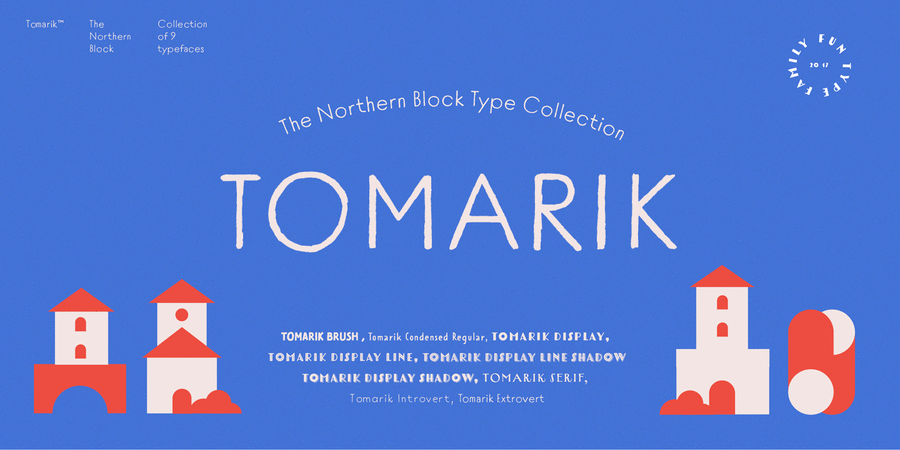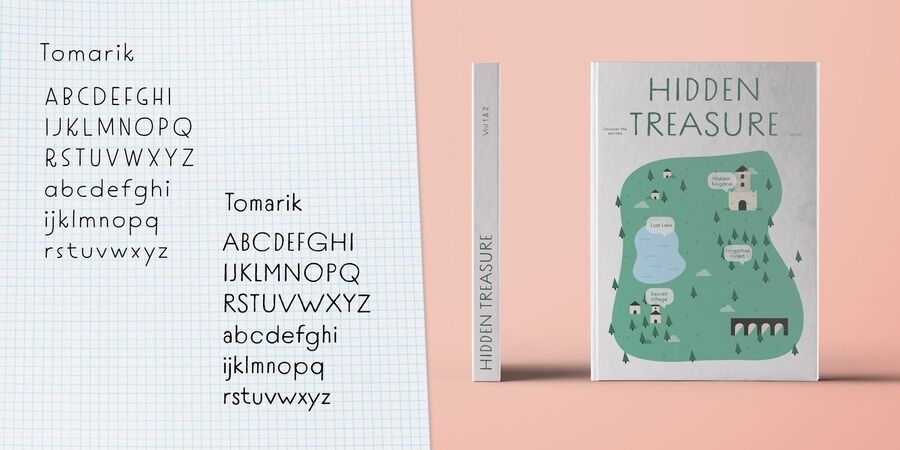
Tomarik Introvert (1 шрифт)
Закритий геометричний гротеск, намальований ручкою чи олівцем – частина яскравої колекції рукописних шрифтів Томарік. Грайливе доповнення будь-якого творчого проекту. Шрифтової набір, зібраний для роботи за принципом «обирай і змішуй», він пропонує велику різноманітність стилів і характерів. Томарік містить дев'ять різних накреслень з латинкою та кирилицею і включає функції OpenType, такі як верхні та нижні індекси і дроби. Шрифт розробила Марія Пігулевська у 2017 році. Tomarik™ є торговою маркою компанії The Northern Block.
Асоціації з сімейством шрифтів Tomarik IntrovertОсобистість і характер гарнітури:
теплий, затишний, рукотворний, кустарний, саморобний, оригінальний, модний, живий, характерний, доброзичливий, дитячий, приємний, наївний, грайливий, потішний, ламповий, милий, прикольний, мультяшний, вернакулярний, круглий, трикутний, позитивний, примітивний, лаконічний, зрозумілий, ясний, міський, шкільний, домашній
дитсадок, відпочинок, гра, кафе, Хюґе, Інстаграм, Місто, іграшка, табір, школа, мультфільм, анімація, дитяча книжка, смузі, канцтовари, олівці, селфі, графіка, ілюстрація, учень, школяр, школярка, дім, спальня, дизайн Гарнітура має ознаки стилів: